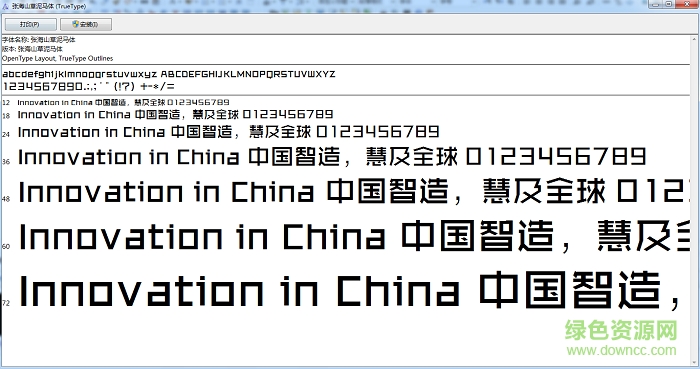
zhscnmt gbk1 0字體又叫張海山草泥馬體,這是一款又特色的中文廣告字體,字形簡潔干凈,方方正正,挺拔端正,辨識度高,喜歡的朋友快來下載吧!
字體特征
字體的藝術(shù)性體現(xiàn)在其完美的外在形式與豐富的內(nèi)涵之中。 字體是文化的載體,是社會的縮影。
zhscnmt gbk1 0字體特點
體剛勁有力,完美無比,可應(yīng)用于卡通設(shè)計、繪畫藝術(shù)、產(chǎn)品創(chuàng)意、平面廣告、印刷包裝等領(lǐng)域!
字型比較粗,具有引人注目的特點,支持英文、數(shù)字輸入轉(zhuǎn)換功能
比例漂亮,清晰度高,非常精致的一款字體!